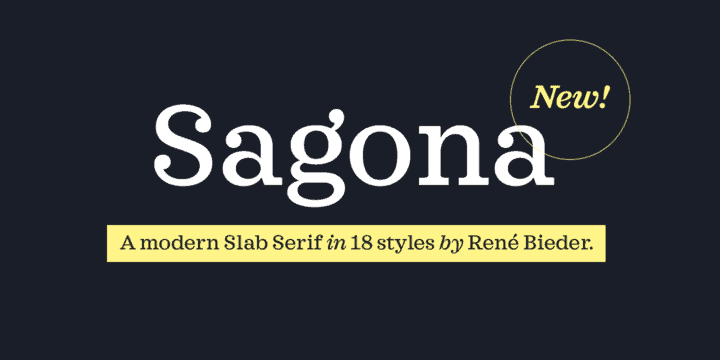
A Sagona Font Family é uma nova adição à família de fontes slab serif que traz ao design gráfico uma versatilidade interessante para tamanhos diversos de texto, desde headlines até textos mais detalhados. Desenvolvida por Rene Bieder, a Sagona surge como um moderno descendente do modelo clarendon/ionic, com influências que remontam ao final da era vitoriana. Similar em muitos aspectos à sua famosa representante, Clarendon, a Sagona se distingue através de suas fortes serifas e contraste variável no traço, resultando num tipo versátil perfeitamente adaptado para headlines. Suas propriedades visuais, tanto as robustas serifas quanto o contraste da linha, permitem que a fonte seja usada em uma ampla gama de aplicativos gráficos. Com Sagona na sua paleta, designers e grafistas podem explorar estilos modernos enquanto mantêm um toque clássico. A fonte é perfeita para destacar elementos-chave em designs, ou para dar um toque personalizado a texturas mais sutis. Como uma slab serif, a Sagona oferece um contraste forte entre as serifas e o fundo semelhante à maioria das suas antecessoras do século passado, combinando modernidade com clareza no design.